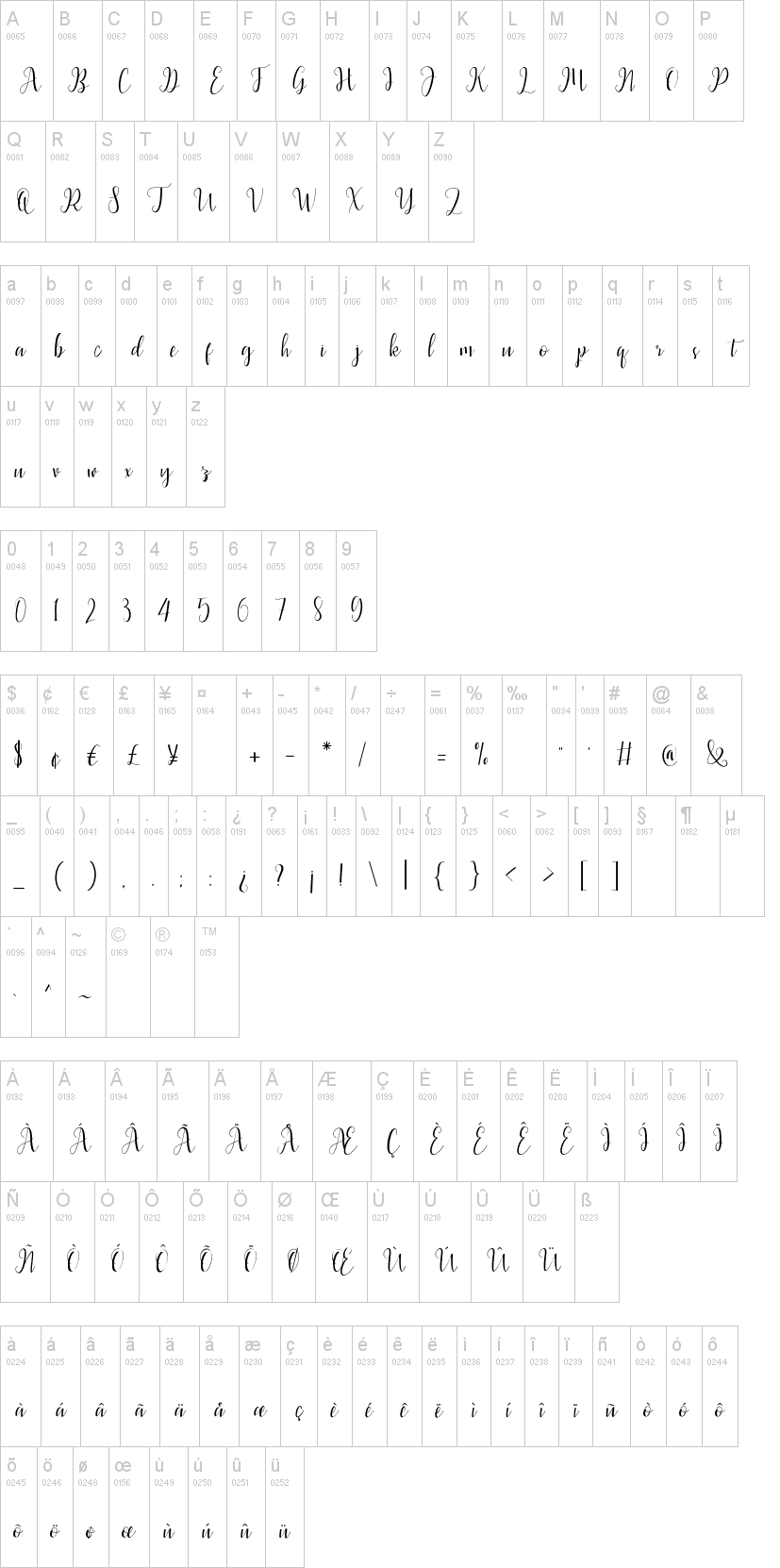
? Latasha Script是一款精致的手写体字体,由Jasmine Ellis创作,它具有优雅的外观和自然的流动。Latasha Script字体设计灵感来源于传统的毛笔书法,具有清新的外观,拥有自然的笔画和曲线,更易于阅读。它可以用于设计海报、书籍封面、礼品卡片等,也可以用于网页设计,以及印刷品设计,更能让你的设计更加生动有趣。内容介绍
Latasha Script是一款非常不错的手写艺术字体,具有很好的视觉感,适合于文化类的宣传设计、商业类品牌的广告和产品包装设计以及个性化文字排版等较多场景。